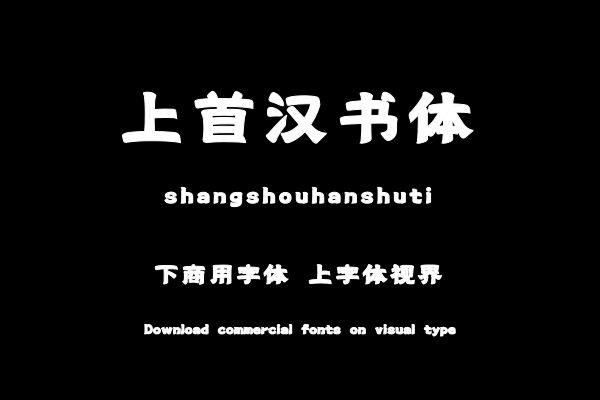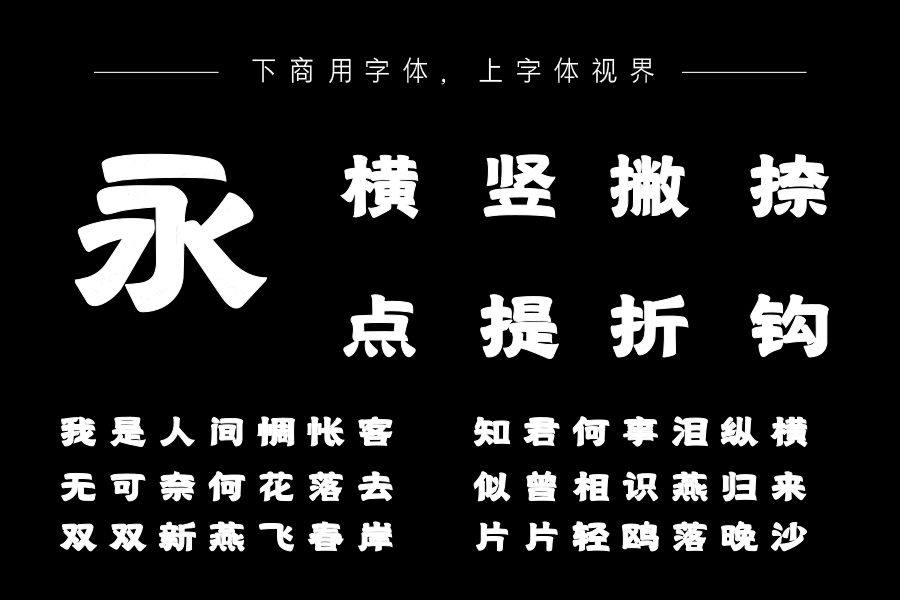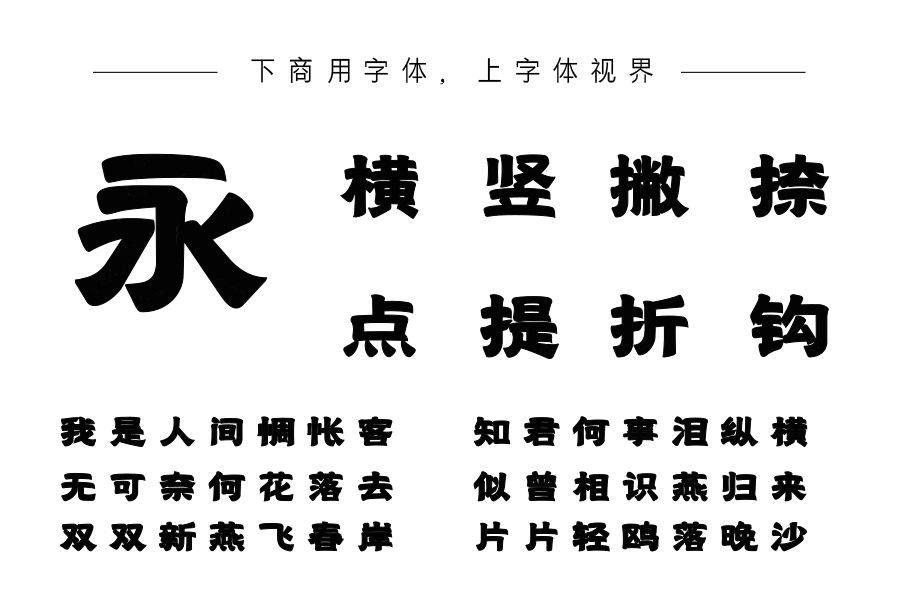
上首汉书体,字体古朴雄浑,笔画流畅且竖画粗壮稳重。在结构上,兼具隶书的部分特色,字体多呈扁方形,横向舒展,左右开张,给人以稳重、宽博之感。购买须知:“下载服务费”与“字体VIP”所获得字体 仅用于个人非商用, 商用请联系付费授权。本字体为电脑用字,手机没有root权限不支持直接手机换字(手机如何root,请自行百度搜索教程)。购买前请先 了解清楚后再付款 ,字体为虚拟产品无法回收 一旦购买不支持退款。